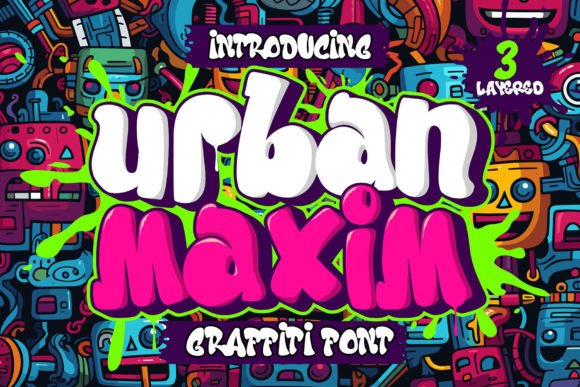
Urban Maxim
適切なデザイン要素を見つけるのは難しい場合がありますが、Urban Maximは作品を即座に引き立てる優れたコレクションを提供します。
精密に作られたUrban Maximは、クリーンなベクター、滑らかなタイポグラフィ、そして安心のための商用ライセンスを提供します。
POD(オンデマンド印刷)製品、結婚式の招待状、またはソーシャルメディアのグラフィックを作成している場合でも、Urban Maximは理想的です。